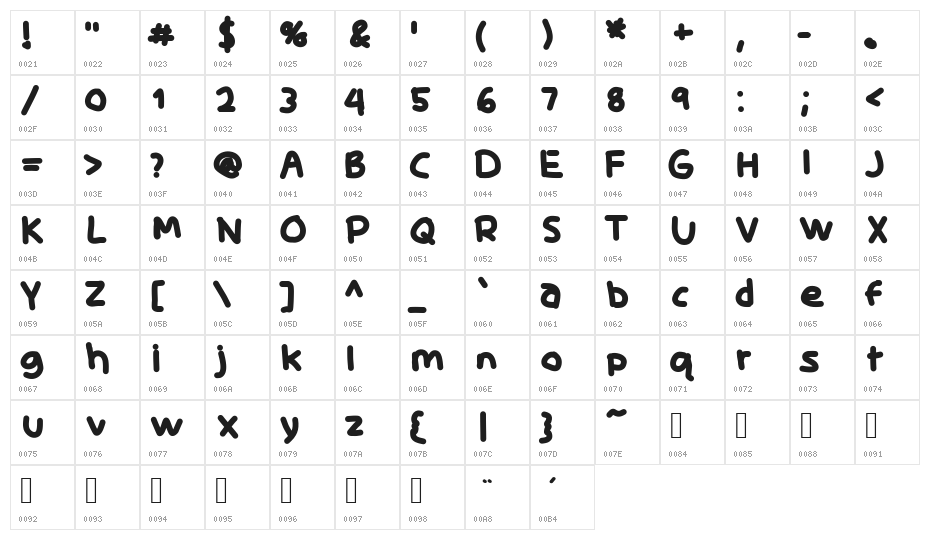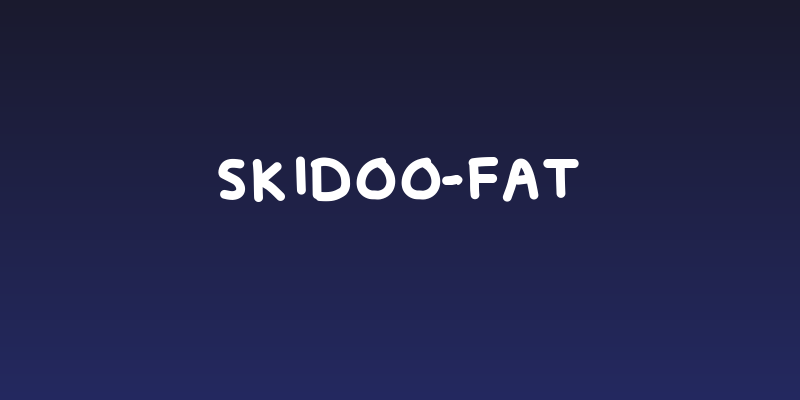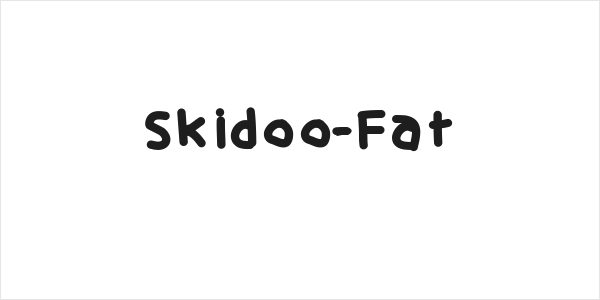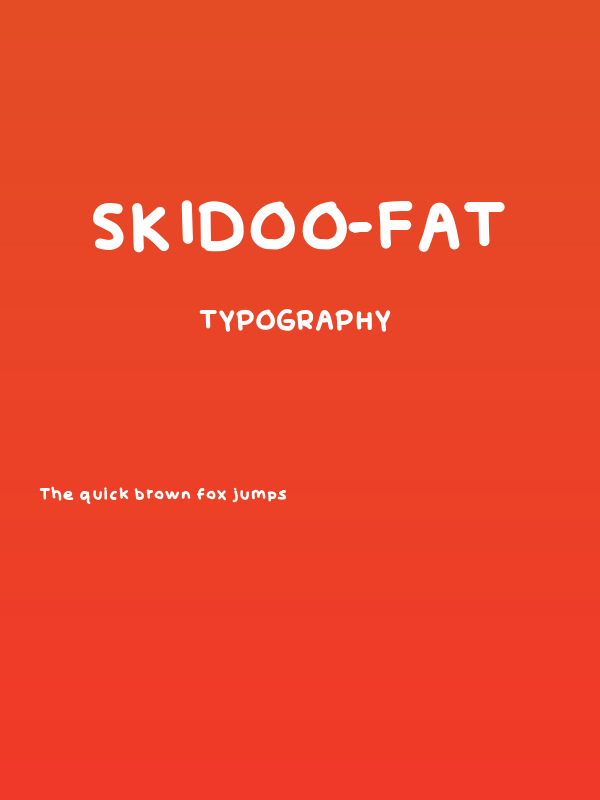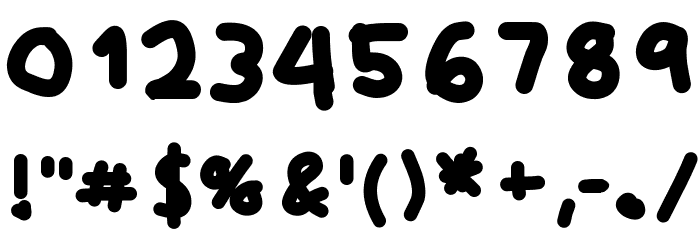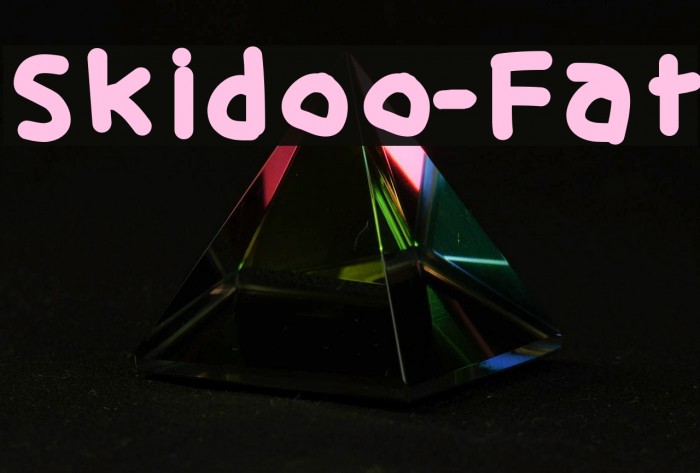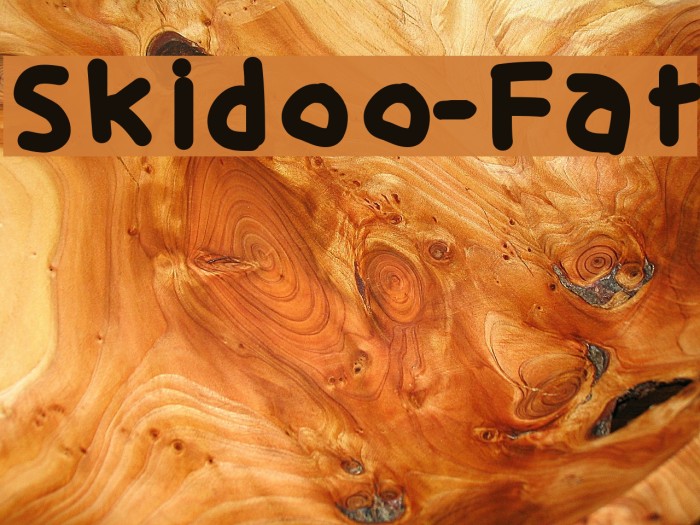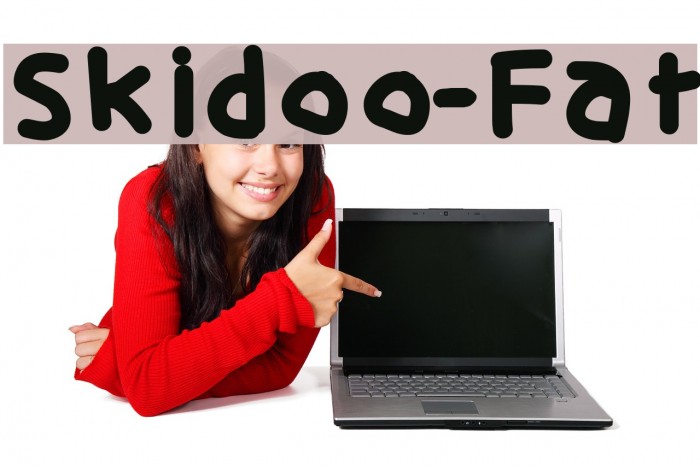
Skidoo-Fat Font
Robothaus - Patrick McGrath - robothaus.com
| Estilo general | Playful |
| Caso de uso | Headlines, Logos, Informal Text |
| Proyectos propuestos | Ideal for children's books, playful branding, casual invitations, and social media graphics. |